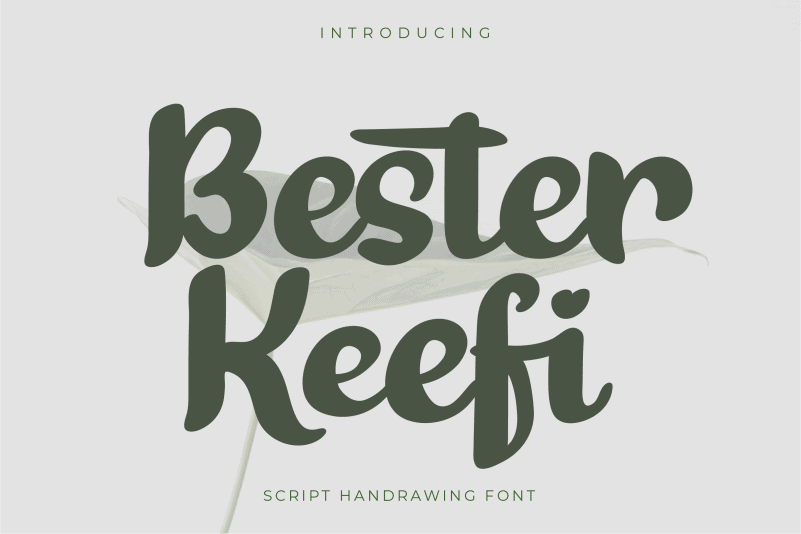
Bester Keefi Script Font – Download Grátis
A fonte Bester Keefi Script é uma deliciosa mistura de estilo script e calligrafia que traz para você uma experiência única na hora de criar arte digital. Desenvolvida por twinletter, esta fonte vem embalada com um design elegante e sofisticado, ideal para personalizar textos em websites, impressões ou até mesmo como elementos gráficos. Esse é um projeto gratuito que oferece a você uma experiência gratuita pessoalmente sem custos adicionais. Se você achar útil e se sentir confortável, sua doação é muito bem vinda através da conta PayPal: https://paypal.me/abahrozi. Este site não pretende lucrar com esses recursos gratuitos para download; seu apoio será extremamente apreciado. Com Bester Keefi Script Font, você tem a possibilidade de trazer uma sensação única e impecável ao seu design, seja criando letras personalizadas ou incorporando elementos visuais perfeitamente elegantes. Esta fonte é um excelente recurso para designers gráficos que buscam adicionar um toque único e artístico à sua produção.